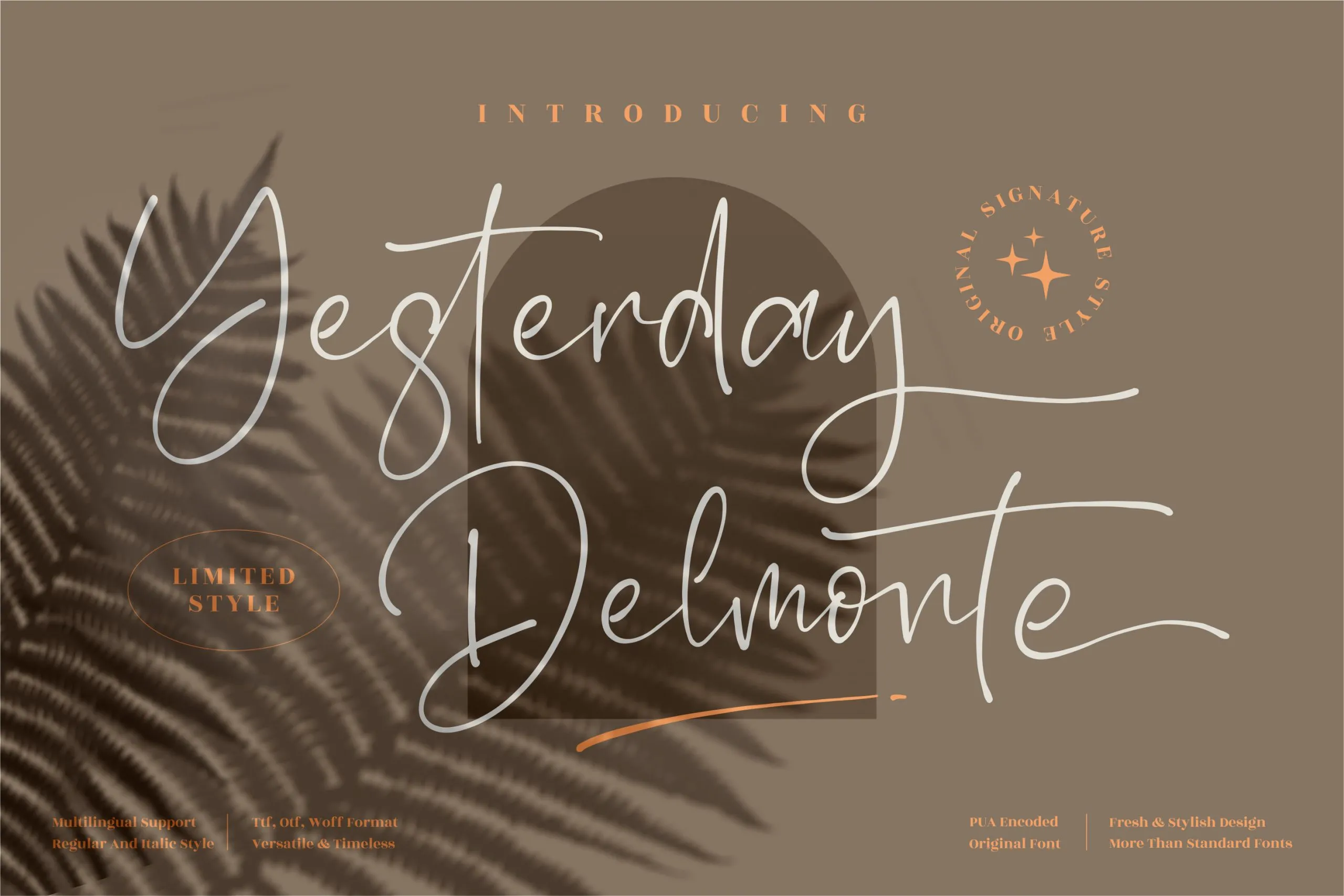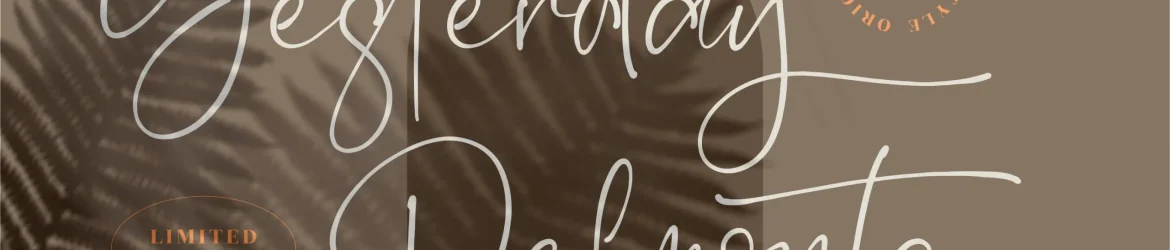
A fonte ‘Yesterday Delmonte Font’ é uma elegante escolha para aqueles que procuram uma assinatura única e sofisticada, ideal para um vasto espectro de projetos criativos. Desenvolvida pelo designer perspectype, ela combina características fluidas e elegantes em harmonia perfeita com os estilos mais requintados. A sua elegância não se limita apenas aos logotipos ou materiais de embalagem de luxo; a ‘Yesterday Delmonte Font’ também brilha sob o penumbra das criações gráficas para cartões de convite, cartões de felicitação e até mesmo nas etiquetas. Essa fonte perfeita para todos os tipos de projetos pode deixar seus trabalhos com um toque final único e autêntico, fazendo delas verdadeiras obras de arte. Além disso, sua versão handwritten torna-a ainda mais acessível para aqueles que buscam uma assinatura personalizada em cada projeto, sejam eles design editorial, impressões digitais ou trabalhos artesanais. Sua versatilidade é semelhante à sua riqueza e profundidade, tornando-a um dos principais ativos do seu portfólio de recursos gráficos.